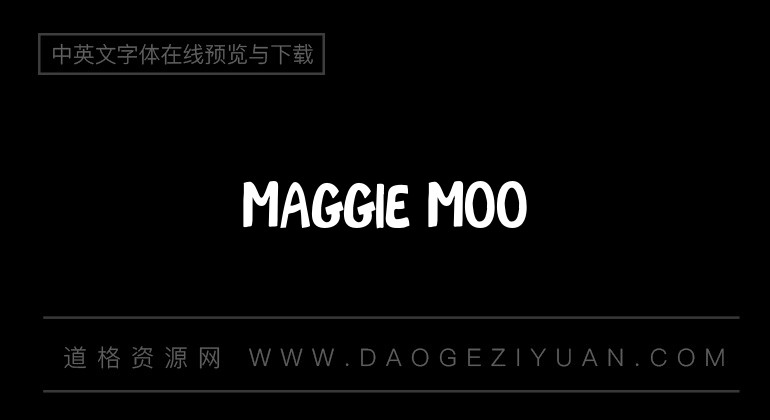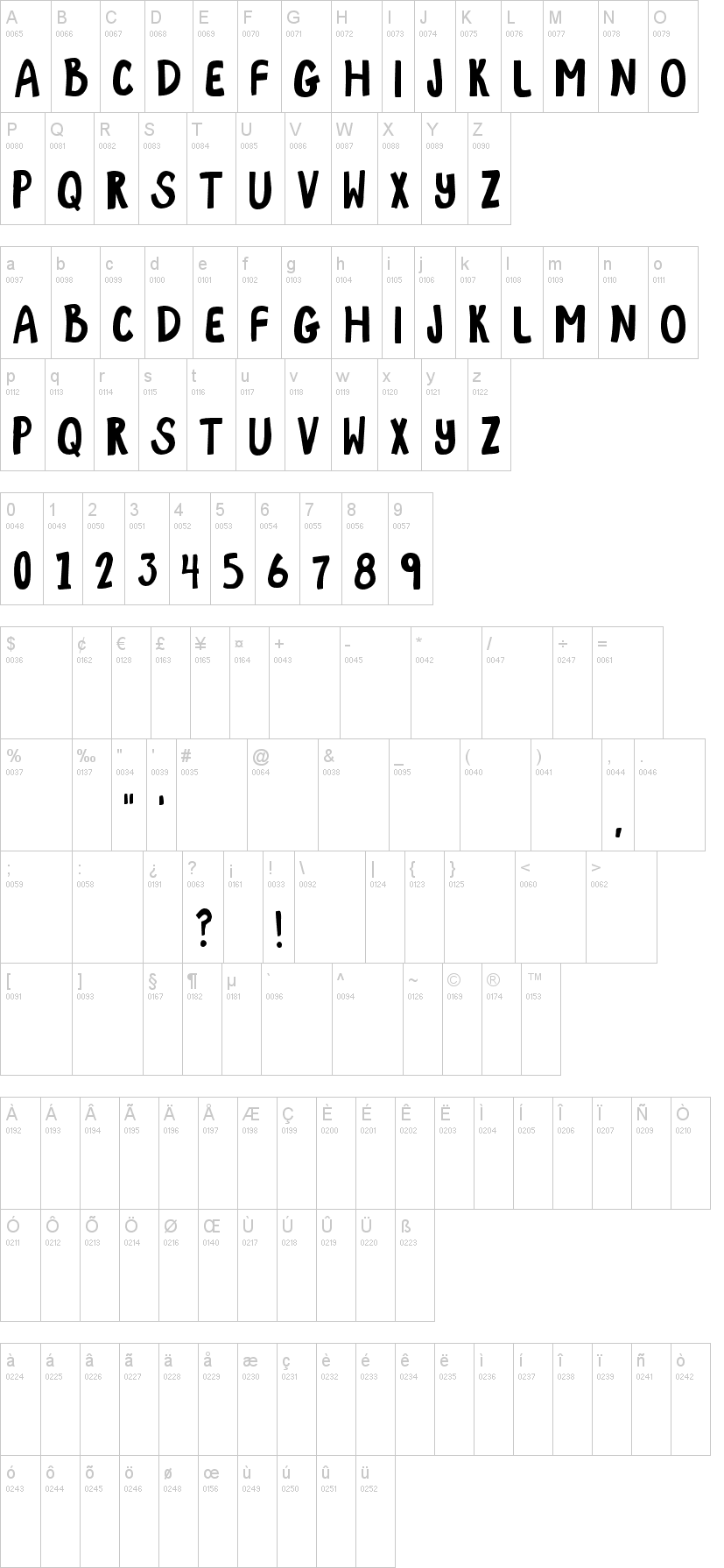
Maggie Moo 是一种可爱的手写风格字体,其字母形状类似于儿童手写或漫画书中常见的字母形状。它由设计师 Misti's Fonts 设计并出版,可在许多字体网站和商店中找到。 Maggie Moo 字体包含大写字母、小写字母、数字和标点符号,具有轻快、活泼的氛围,适用于许多场合,如儿童书籍、广告、网站设计和贺卡等。该字体的特点是线条柔和,符号简单,字母间距适中,易于阅读和使用。内容介绍
Maggie Moo是一款非常不错的手写艺术字体,具有很好的视觉感,适合于文化类的宣传设计、商业类品牌的广告和产品包装设计以及个性化文字排版等较多场景。